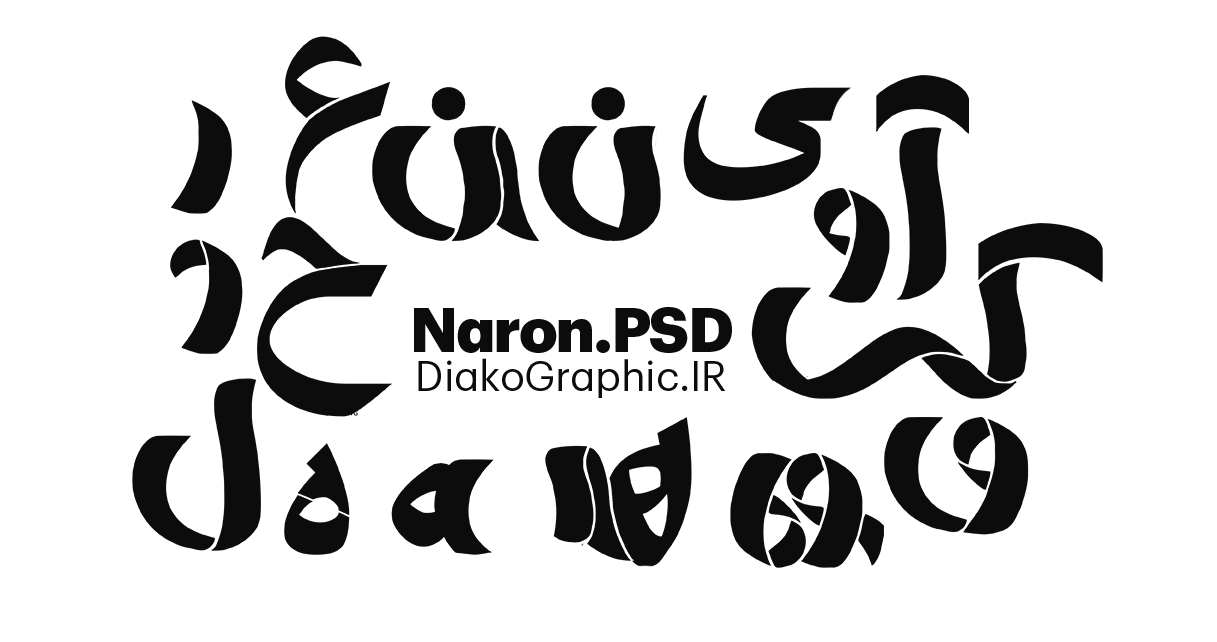
فونت تایپوگرافی نارون Naron Font
فونت تایپوگرافی فارسی نارون یکی دیگر از مجموعه فونت های تایپوگرافی سایت دیاکو گرافیک می باشد. که این فونت به صورت فایل لایه باز PSD عرضه…
فونت تایپوگرافی فارسی نارون یکی دیگر از مجموعه فونت های تایپوگرافی سایت دیاکو گرافیک می باشد. که این فونت به صورت فایل لایه باز PSD عرضه شده است که امکان استفاده در نرم افزار فتوشاپ برای تایپوگرافی به خصوص طراحی لوگو تایپ می باشد.
فونت لوگوتایپ نارون
فونت نارون مناسب استفاده در تایپوگرافی های حرفه ای و طراحی لوگو تایپ می باشد که کار طراحان گرافیک و حتی کسانی که دانش طراحی ندارند در این زمینه آسان می سازد. برخی ویژگی های فونت نارون را مرور میکنیم:
- شامل تمام حروف الفبای فارسی